YOU WILL FOREVER BE MY ALWAYS
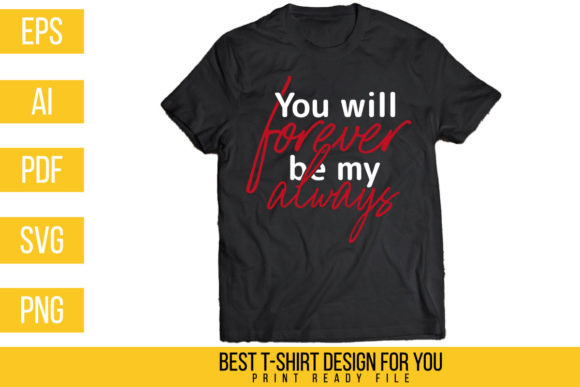
Mencari elemen desain yang tepat bisa jadi sulit, namun YOU WILL FOREVER BE MY ALWAYS menawarkan koleksi luar biasa yang akan langsung meningkatkan kualitas karya Anda.
Dibuat dengan presisi, YOU WILL FOREVER BE MY ALWAYS menyediakan vektor yang bersih, tipografi yang halus, serta lisensi komersial untuk ketenangan pikiran Anda.
Baik Anda membuat produk POD (Print on Demand), undangan pernikahan, atau grafis media sosial, YOU WILL FOREVER BE MY ALWAYS adalah pilihan yang sangat ideal.